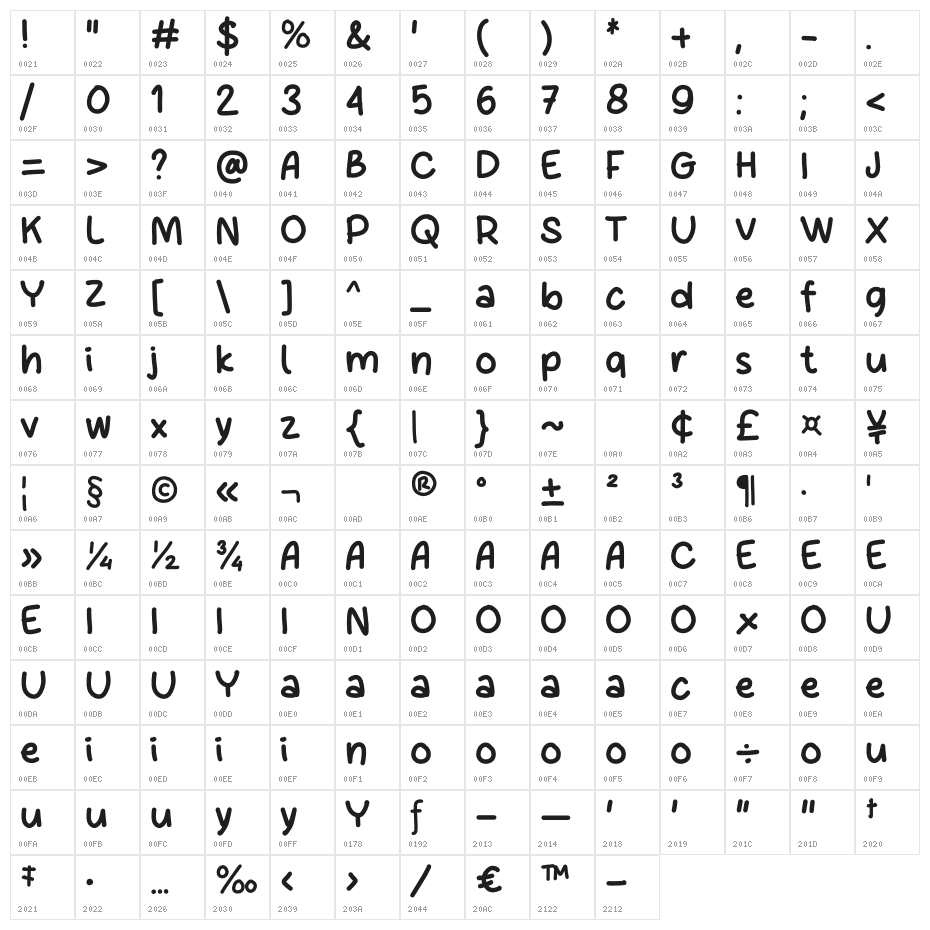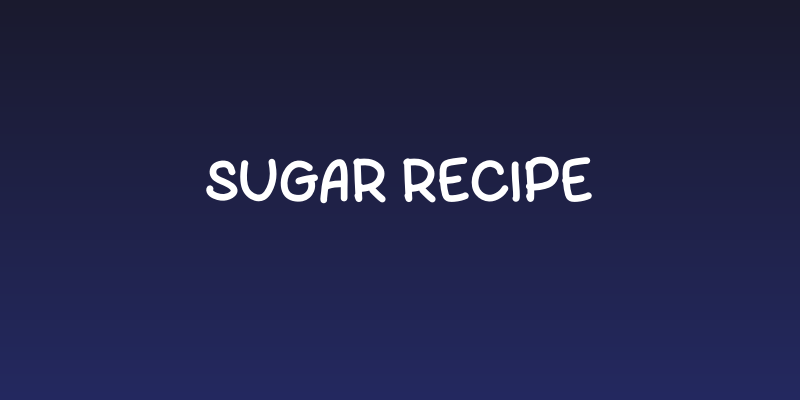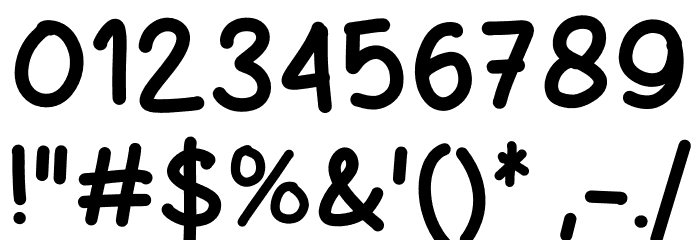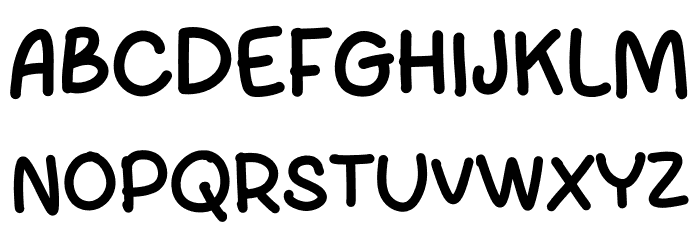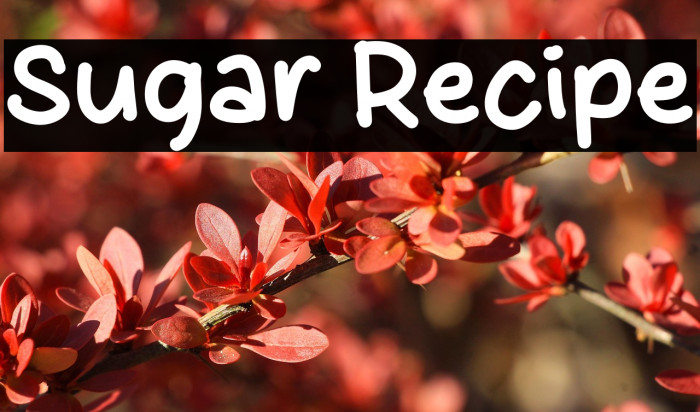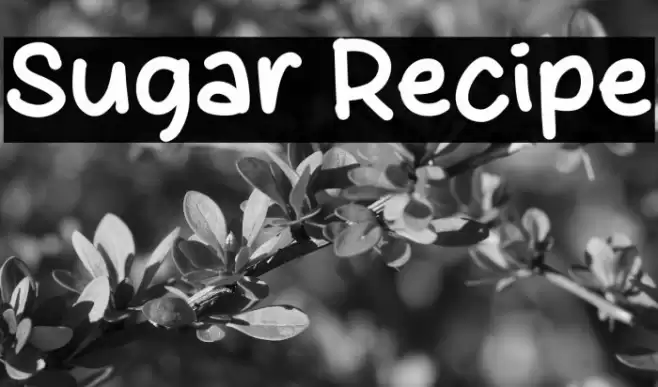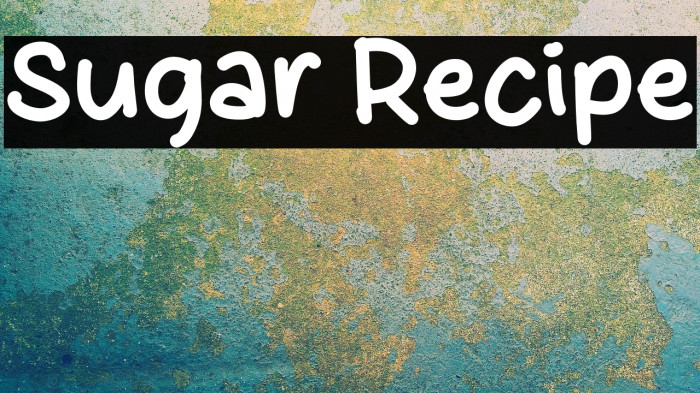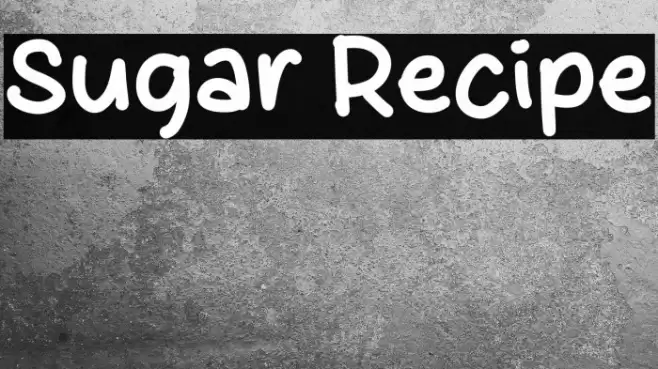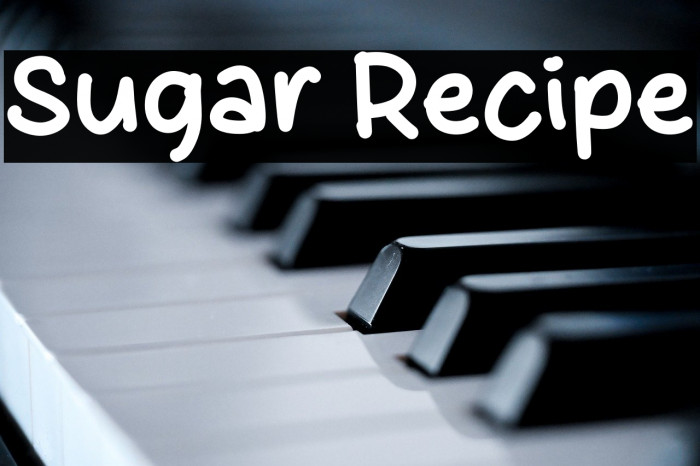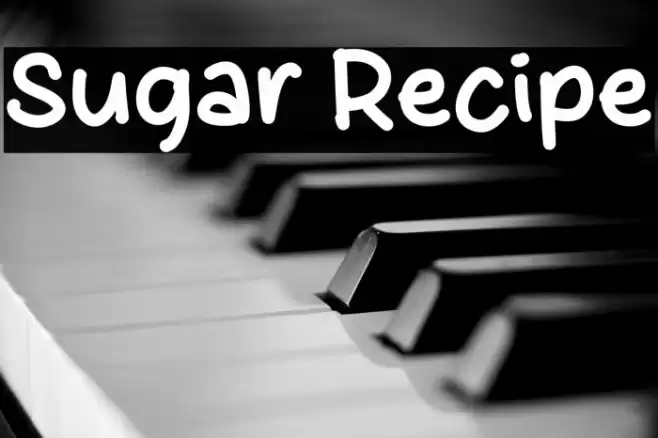
Sugar Recipe Font
| Gesamtstil | Casual |
| Anwendungsfall | Headlines, Logos, Informal Text |
| Vorgeschlagene Projekte | Ideal for children's books, greeting cards, playful branding, and casual invitations. |